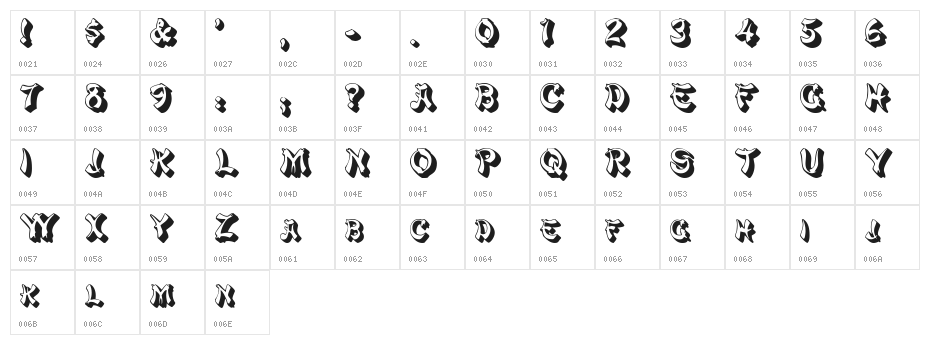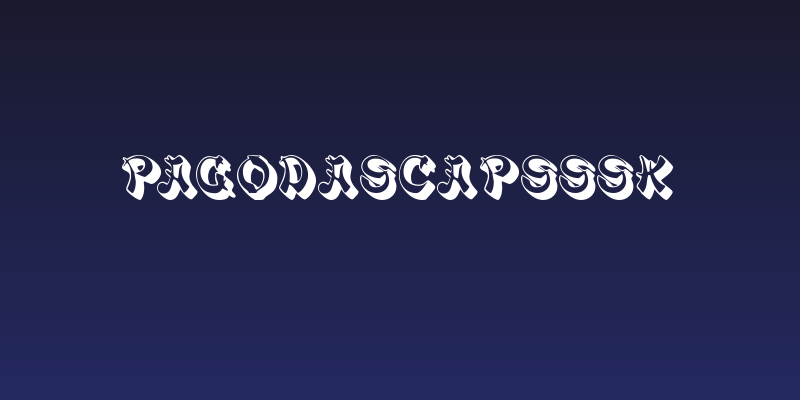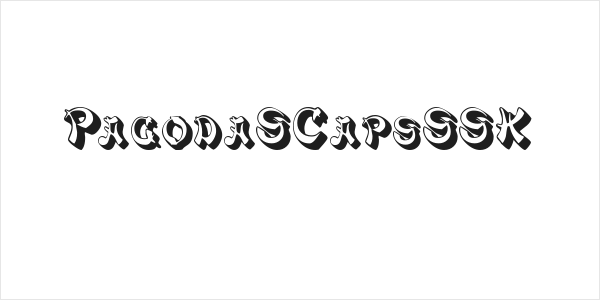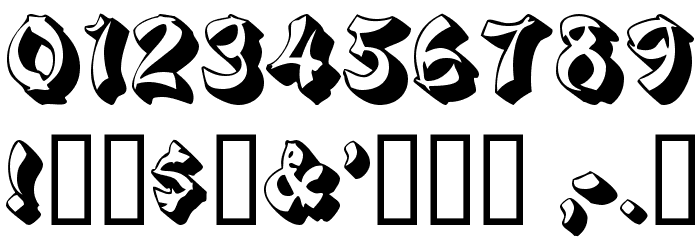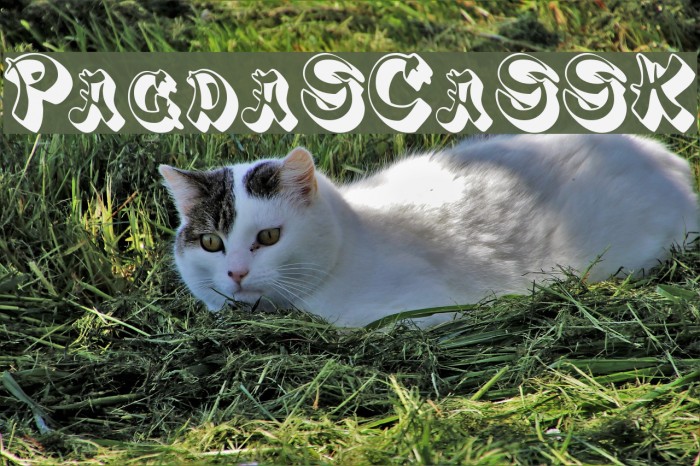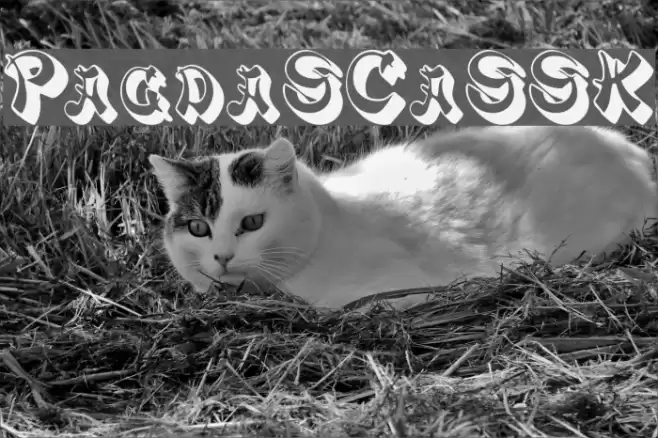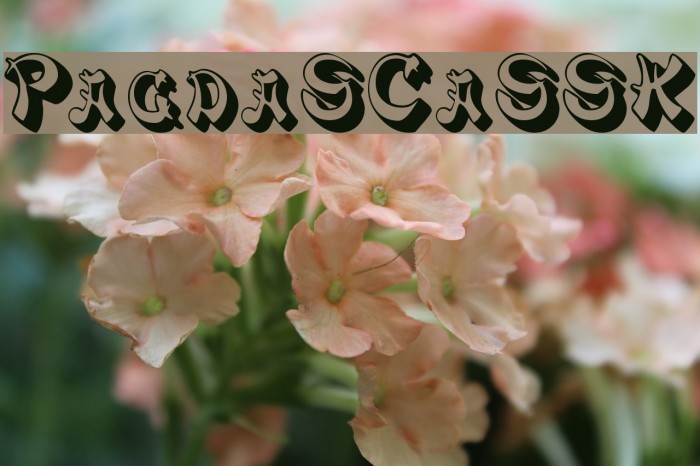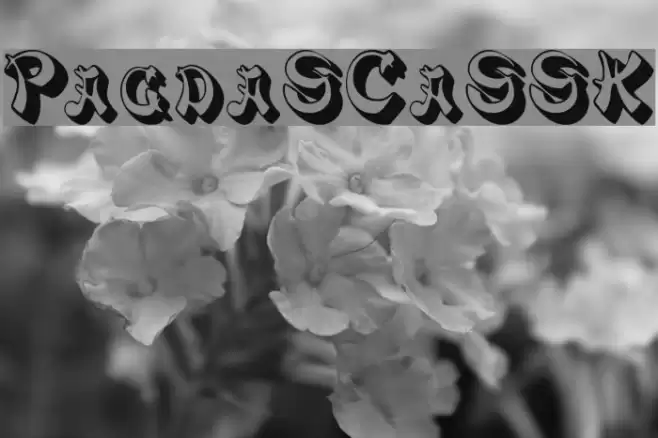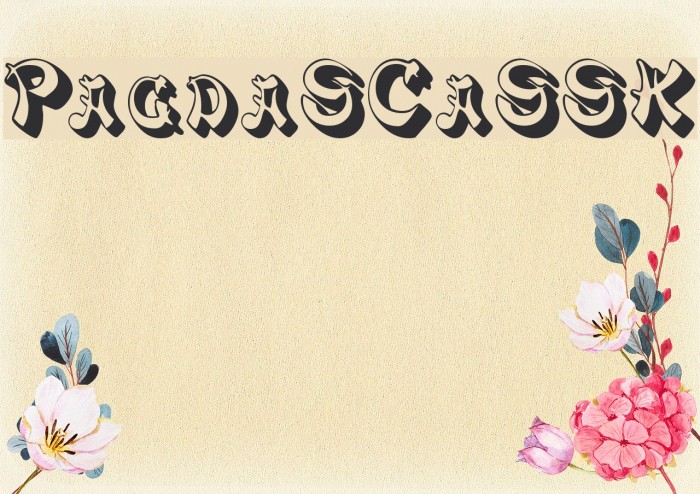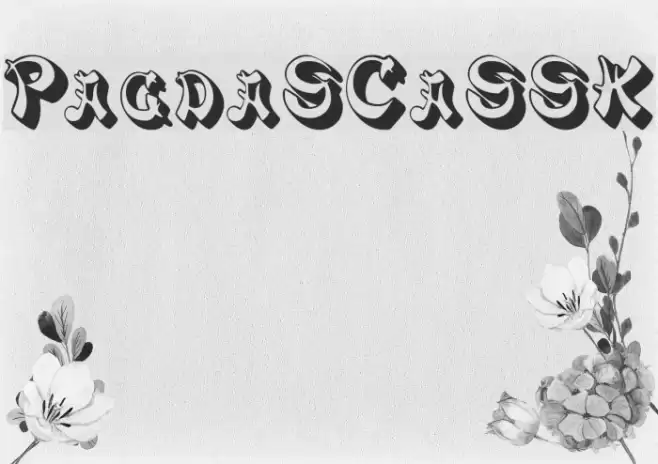
PagodaSCapsSSK Font
PAGODASCAPSSSK أحرف كبيرة
PAGODASCAPSSSK أحرف صغيرة
PAGODASCAPSSSK محارف أخرى
| مشاريع مقترحة | Ideal for use in branding, posters, and headlines where a dramatic and historical aesthetic is desired. |